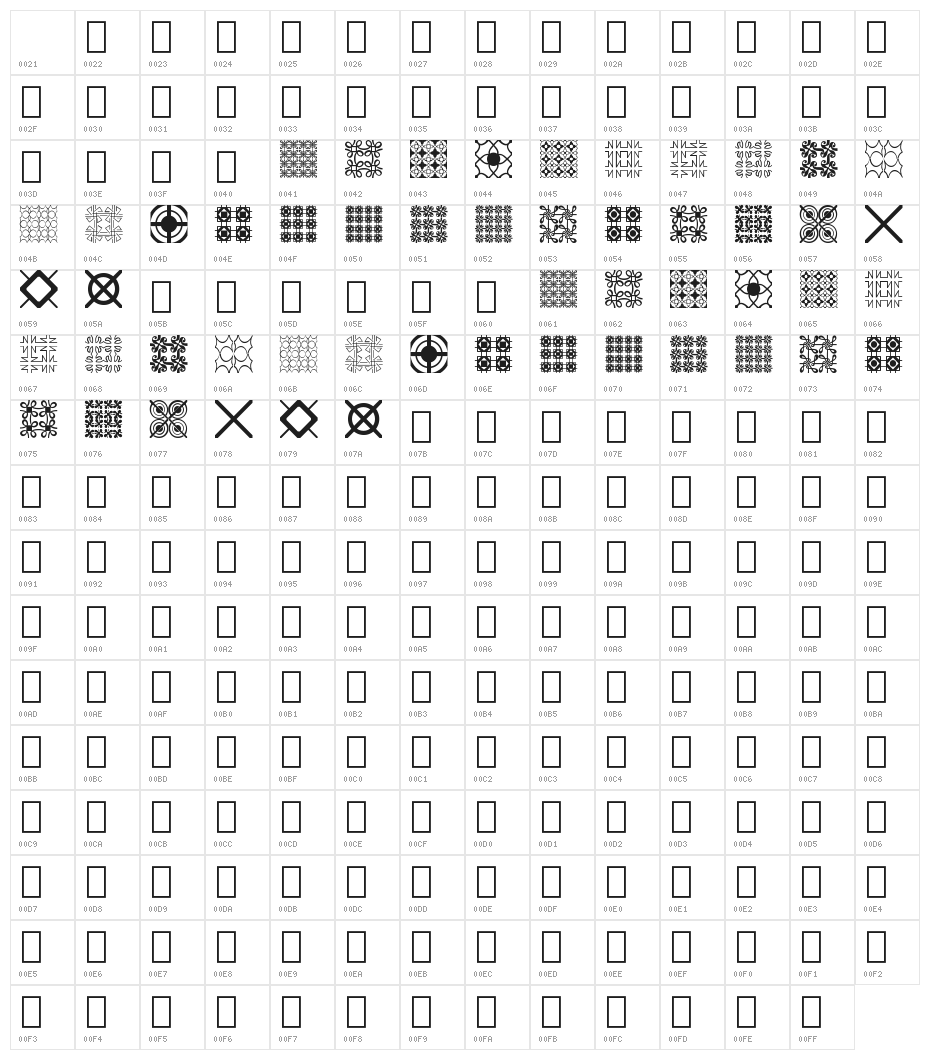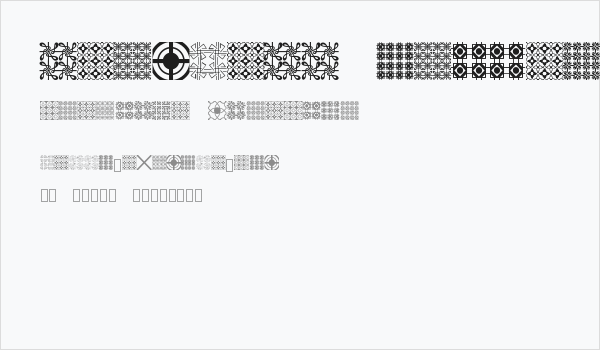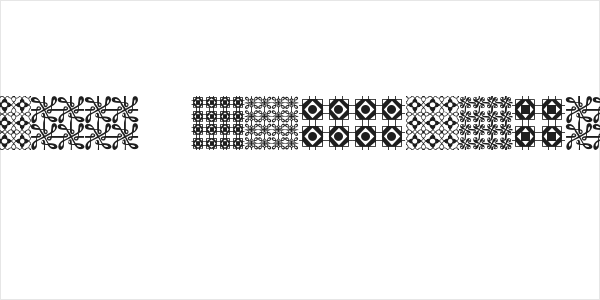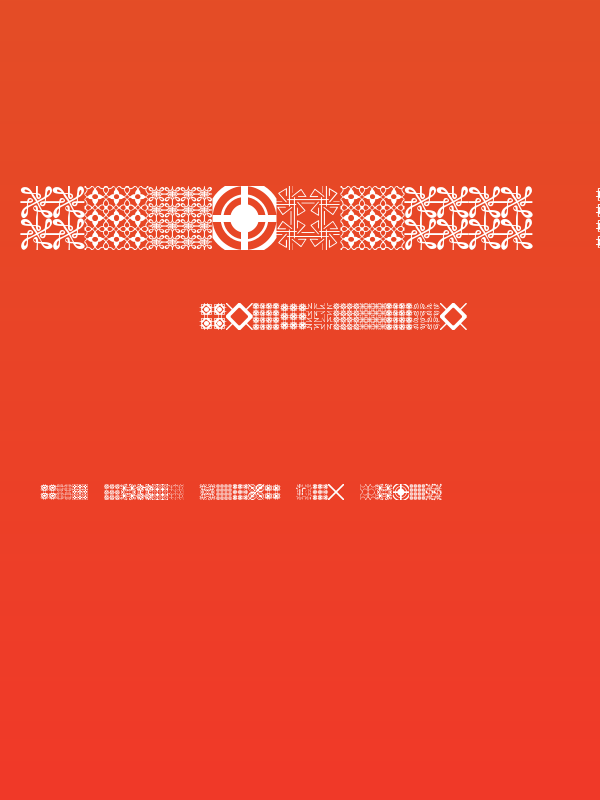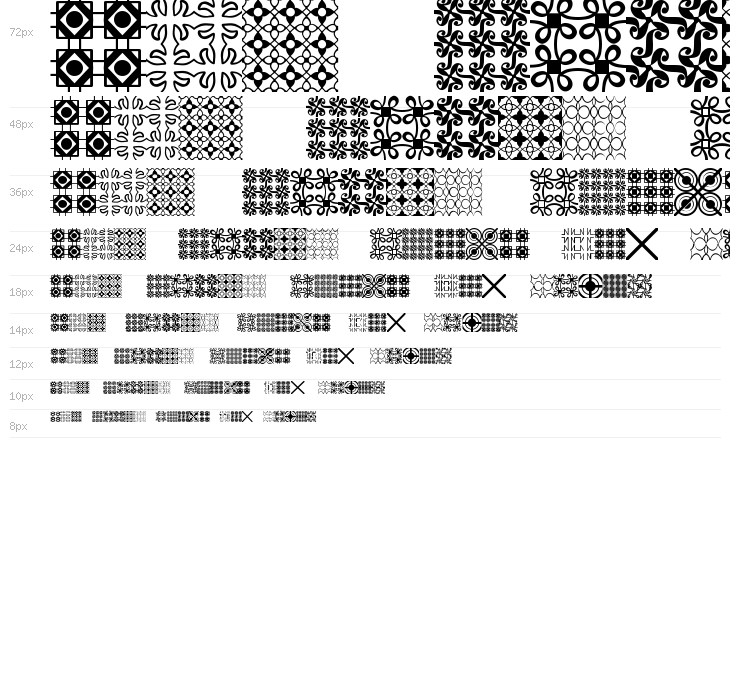
Seamless Patterns Demo Font
| Общий стиль | Decorative, Ornamental, Geometric |
| Область применения | Borders, decorative accents, pattern creation, display purposes |
| Рекомендуемые проекты | Borders, packaging, invitations, digital scrapbooking, textile design, ornamental dividers. |
Seamless Patterns Demo